5 เทคนิคเลือกฟอนต์ป้ายและฉลาก ให้อ่านง่าย ดึงดูดลูกค้า
การเลือกรูปแบบตัวอักษร หรือ ฟอนต์ (Font) เป็นองค์ประกอบที่สำคัญอย่างยิ่งในการออกแบบสื่อสิ่งพิมพ์ ไม่ว่าจะเป็นป้ายโฆษณา ฉลากสินค้า หรือเมนูอาหาร การเลือกฟอนต์ที่เหมาะสมไม่เพียงแต่ช่วยให้ข้อมูลอ่านง่าย แต่ยังสามารถสื่อสารถึงบุคลิกของแบรนด์ สร้างความน่าเชื่อถือ และดึงดูดความสนใจของลูกค้าได้ตั้งแต่แรกเห็น
หัวใจสำคัญของการออกแบบ: ทำไมฟอนต์จึงตัดสินยอดขาย
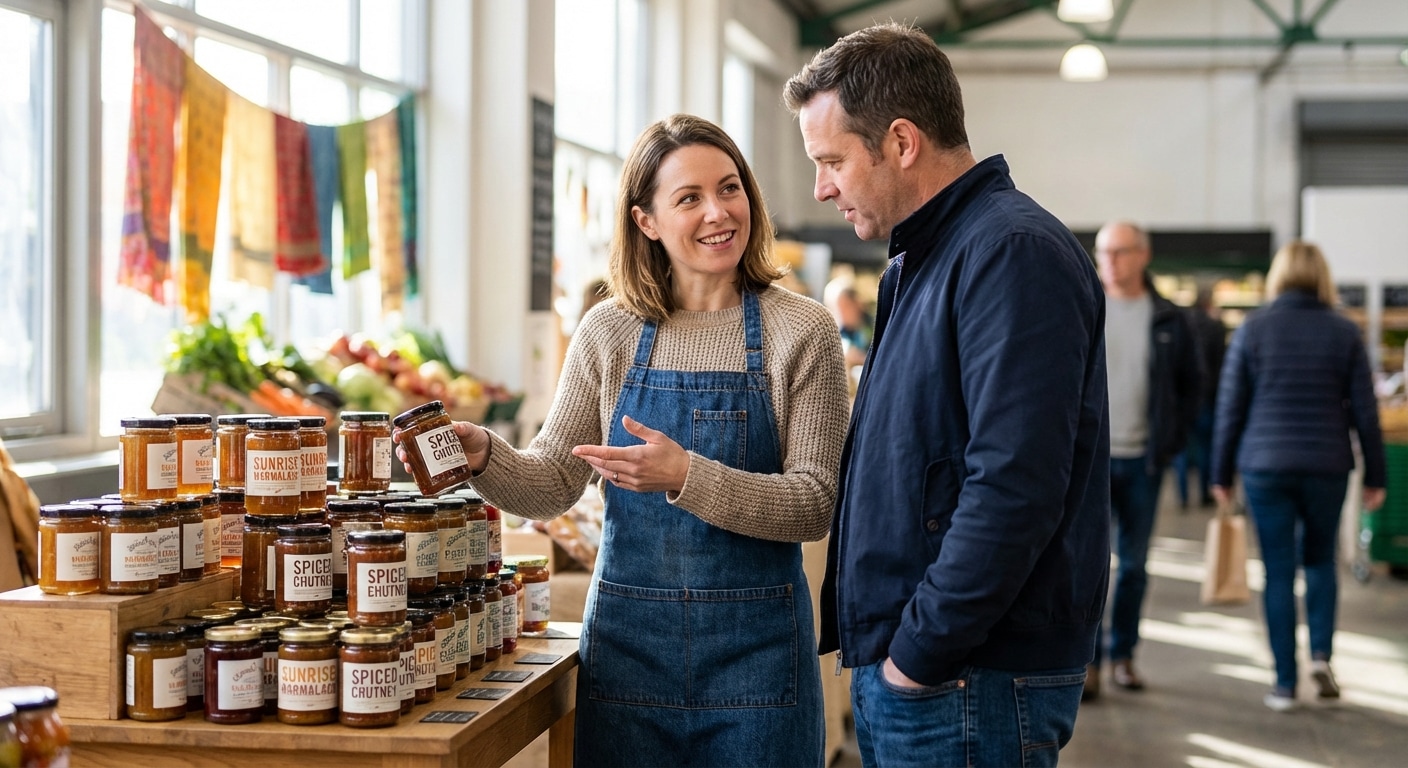
ฟอนต์เปรียบเสมือน “เสียง” ของแบรนด์ที่สื่อสารกับลูกค้าโดยไม่ต้องเอ่ยคำพูด ฟอนต์ที่อ่านยาก ซับซ้อน หรือไม่เข้ากับภาพลักษณ์สินค้า อาจสร้างความสับสนและทำให้ผู้บริโภคมองข้ามผลิตภัณฑ์ไปอย่างน่าเสียดาย โดยเฉพาะสำหรับธุรกิจ SME ที่การสร้างความประทับใจแรกเป็นสิ่งสำคัญอย่างยิ่ง การลงทุนเวลาในการเลือกฟอนต์จึงเป็นการลงทุนที่คุ้มค่าเพื่อเพิ่มโอกาสทางธุรกิจและสร้างการจดจำในระยะยาว
- สื่อสารบุคลิกแบรนด์: ฟอนต์สามารถบอกได้ว่าแบรนด์ของคุณเป็นแบบไหน เช่น จริงจัง, สนุกสนาน, หรูหรา, หรือเป็นกันเอง
- เพิ่มความสามารถในการอ่าน: ฟอนต์ที่ชัดเจนและอ่านง่ายช่วยให้ลูกค้าเข้าใจข้อมูลสำคัญเกี่ยวกับสินค้าได้อย่างรวดเร็ว
- สร้างการจดจำ: ฟอนต์ที่เป็นเอกลักษณ์ช่วยให้ลูกค้าจดจำแบรนด์ของคุณได้ท่ามกลางคู่แข่งมากมาย
- ดึงดูดกลุ่มเป้าหมาย: การเลือกฟอนต์ที่สอดคล้องกับรสนิยมของกลุ่มเป้าหมายช่วยสร้างความเชื่อมโยงและความรู้สึกที่ดีต่อแบรนด์
- เพิ่มความน่าเชื่อถือ: การออกแบบที่ดูเป็นมืออาชีพและใส่ใจในรายละเอียดเล็กๆ น้อยๆ อย่างฟอนต์ ช่วยสร้างความไว้วางใจให้กับลูกค้า
แก่นแท้ของ 5 เทคนิคเลือกฟอนต์ป้ายและฉลาก ให้อ่านง่าย ดึงดูดลูกค้า
การเรียนรู้ 5 เทคนิคเลือกฟอนต์ป้ายและฉลาก ให้อ่านง่าย ดึงดูดลูกค้า ถือเป็นทักษะพื้นฐานที่สำคัญสำหรับผู้ประกอบการและนักออกแบบทุกคน ฟอนต์ที่ถูกเลือกมาอย่างดีจะทำหน้าที่เป็นพนักงานขายเงียบที่ช่วยนำเสนอสินค้าของคุณบนชั้นวางหรือในสายตาของผู้คนที่ผ่านไปมาได้อย่างมีประสิทธิภาพ หลักการสำคัญคือการสร้างสมดุลระหว่างความสวยงามและความชัดเจนในการสื่อสาร เพื่อให้ข้อความสำคัญถูกส่งต่อไปยังผู้บริโภคได้อย่างครบถ้วนและรวดเร็วที่สุด ตั้งแต่ชื่อแบรนด์ไปจนถึงรายละเอียดส่วนผสมหรือโปรโมชั่นพิเศษ ทุกตัวอักษรล้วนมีบทบาทในการตัดสินใจซื้อของลูกค้า
สำหรับธุรกิจที่ต้องการสร้างความโดดเด่น การออกแบบป้ายโฆษณาและฉลากสินค้าจึงไม่ใช่แค่การใส่ข้อมูลให้ครบถ้วน แต่คือการสร้างสรรค์งานศิลปะที่ต้องคำนึงถึงจิตวิทยาผู้บริโภค การเลือกฟอนต์ที่เหมาะสมจะช่วยนำสายตาไปยังจุดที่ต้องการเน้น สร้างลำดับชั้นของข้อมูล และกระตุ้นอารมณ์ความรู้สึกที่สอดคล้องกับตัวผลิตภัณฑ์ ไม่ว่าจะเป็นความรู้สึกอบอุ่นน่าเชื่อถือของสินค้าโฮมเมด หรือความรู้สึกทันสมัยน่าตื่นเต้นของสินค้าเทคโนโลยี ฟอนต์คือเครื่องมือสำคัญที่ช่วยให้การสื่อสารนั้นสมบูรณ์แบบ
เจาะลึก 5 กลยุทธ์การเลือกฟอนต์ฉบับมืออาชีพ
การเลือกฟอนต์ไม่ใช่เรื่องของความชอบส่วนตัว แต่เป็นกระบวนการที่ต้องอาศัยทั้งศาสตร์และศิลป์ เพื่อให้ได้ผลลัพธ์ที่ตอบโจทย์ทั้งในด้านการตลาดและการออกแบบ ต่อไปนี้คือการเจาะลึก 5 เทคนิคสำคัญที่จะช่วยยกระดับงานออกแบบป้ายและฉลากของคุณ
เทคนิคที่ 1: เลือกประเภทฟอนต์ให้สะท้อนตัวตนของแบรนด์
ประเภทของฟอนต์ส่งผลโดยตรงต่อการรับรู้ของลูกค้า การเลือกประเภทฟอนต์ที่สอดคล้องกับบุคลิกของสินค้าและกลุ่มเป้าหมายจึงเป็นขั้นตอนแรกที่สำคัญที่สุด
- ฟอนต์มีหัว (Serif): ฟอนต์ประเภทนี้จะมีขีดเล็กๆ ที่ปลายตัวอักษร ให้ความรู้สึกคลาสสิก เป็นทางการ น่าเชื่อถือ และดั้งเดิม เหมาะสำหรับสินค้าที่ต้องการสร้างความไว้วางใจ เช่น ผลิตภัณฑ์เพื่อสุขภาพ แบรนด์ที่มีประวัติยาวนาน หรือสินค้ากลุ่มพรีเมียม
- ฟอนต์ไม่มีหัว (Sans Serif): เป็นฟอนต์ที่ไม่มีขีดที่ปลายตัวอักษร ดูเรียบง่าย ทันสมัย สะอาดตา และอ่านง่าย เหมาะกับสินค้าเทคโนโลยี แบรนด์แฟชั่นมินิมอล หรือผลิตภัณฑ์ที่ต้องการสื่อถึงความใหม่และความสดใส
- ฟอนต์ลายมือ (Script/Handwritten): ฟอนต์ที่เลียนแบบลายมือเขียน ให้ความรู้สึกเป็นกันเอง อบอุ่น มีความเป็นมนุษย์ และสร้างสรรค์ เหมาะอย่างยิ่งสำหรับธุรกิจคาเฟ่ ร้านอาหาร เบเกอรี่ สินค้าแฮนด์เมด หรือผลิตภัณฑ์ออร์แกนิกที่ต้องการเน้นความเป็นธรรมชาติ
การเลือกประเภทฟอนต์ที่ถูกต้องเปรียบเสมือนการเลือกเสื้อผ้าให้เหมาะกับกาลเทศะ ฟอนต์ที่ใช่จะช่วยส่งเสริมภาพลักษณ์ของแบรนด์ให้โดดเด่นและน่าจดจำ
| คุณลักษณะ | ฟอนต์มีหัว (Serif) | ฟอนต์ไม่มีหัว (Sans Serif) | ฟอนต์ลายมือ (Script) |
|---|---|---|---|
| ภาพลักษณ์ | น่าเชื่อถือ, ดั้งเดิม, เป็นทางการ | ทันสมัย, เรียบง่าย, ชัดเจน | เป็นกันเอง, อบอุ่น, สร้างสรรค์ |
| เหมาะกับธุรกิจ | สินค้าสุขภาพ, แบรนด์หรู, สถาบันการเงิน | เทคโนโลยี, สตาร์ทอัพ, แฟชั่นมินิมอล | คาเฟ่, เบเกอรี่, สินค้าโฮมเมด, การ์ดเชิญ |
| จุดเด่น | อ่านง่ายในเนื้อหายาวๆ (สิ่งพิมพ์) | อ่านง่ายบนหน้าจอและในระยะไกล | สร้างเอกลักษณ์และความรู้สึกส่วนตัว |
เทคนิคที่ 2: น้อยแต่มาก จำกัดจำนวนฟอนต์เพื่อความชัดเจน
หนึ่งในข้อผิดพลาดที่พบบ่อยที่สุดคือการใช้ฟอนต์หลากหลายรูปแบบมากเกินไปในงานออกแบบชิ้นเดียว ซึ่งทำให้ดูรก สับสน และขาดความเป็นมืออาชีพ กฎทองของการออกแบบคือ จำกัดจำนวนฟอนต์ไม่เกิน 2-3 แบบต่อหนึ่งฉลากหรือป้ายโฆษณา
หลักการคือการสร้างลำดับชั้นของข้อมูล (Typographic Hierarchy) โดยใช้ฟอนต์ที่แตกต่างกันเพื่อวัตถุประสงค์ที่ต่างกัน เช่น:
- ฟอนต์หลัก (Primary Font): ใช้สำหรับชื่อแบรนด์หรือหัวข้อที่สำคัญที่สุด ควรเป็นฟอนต์ที่โดดเด่นและสะท้อนบุคลิกของแบรนด์ได้ดีที่สุด